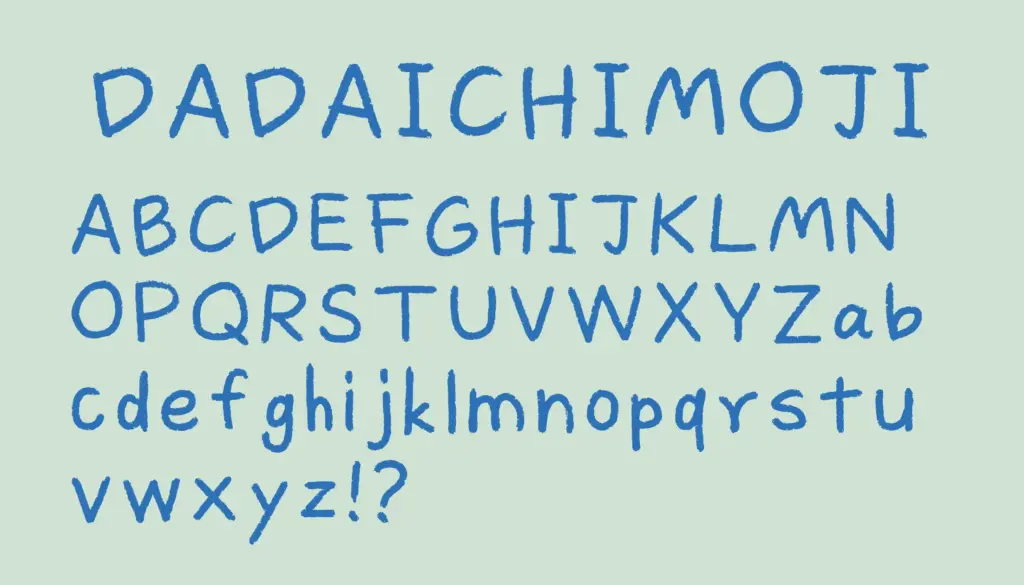
ゆるくて丸みを帯びた筆致が特徴の英字手書きフォント。アルファベットと数字、記号が収録されており、ポップで優しい印象を与えます。クセがあるけれど読みやすく、メッセージカードやSNS投稿、ガーリーなデザインにぴったり。さりげない手書き感と統一感が欲しいときに重宝する、かわいさ満点の英字フォントです。
ダダ壱もじ